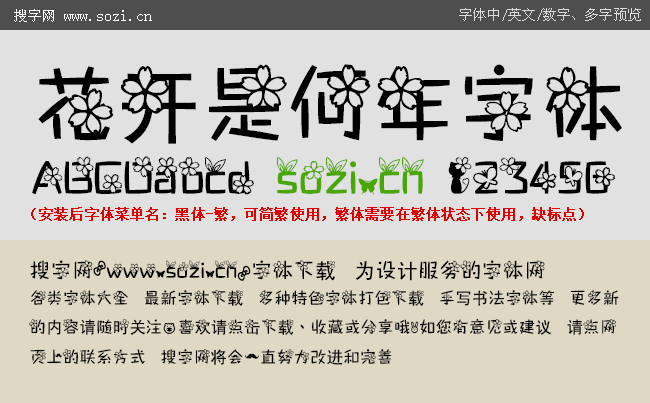
花開(kāi)是何年字體
搜字網(wǎng)給大家提供一款花開(kāi)是何年字體手機(jī)中文字體下載。這款手機(jī)字體是以方正稚藝體為原形,筆畫間插入了漂亮的卡通花朵圖案。方正稚藝體是一款POP風(fēng)格字體,筆畫簡(jiǎn)單可愛(ài),充滿童趣,特別適合喜歡手機(jī)字體個(gè)性一些的朋友在手機(jī)上安裝使用。